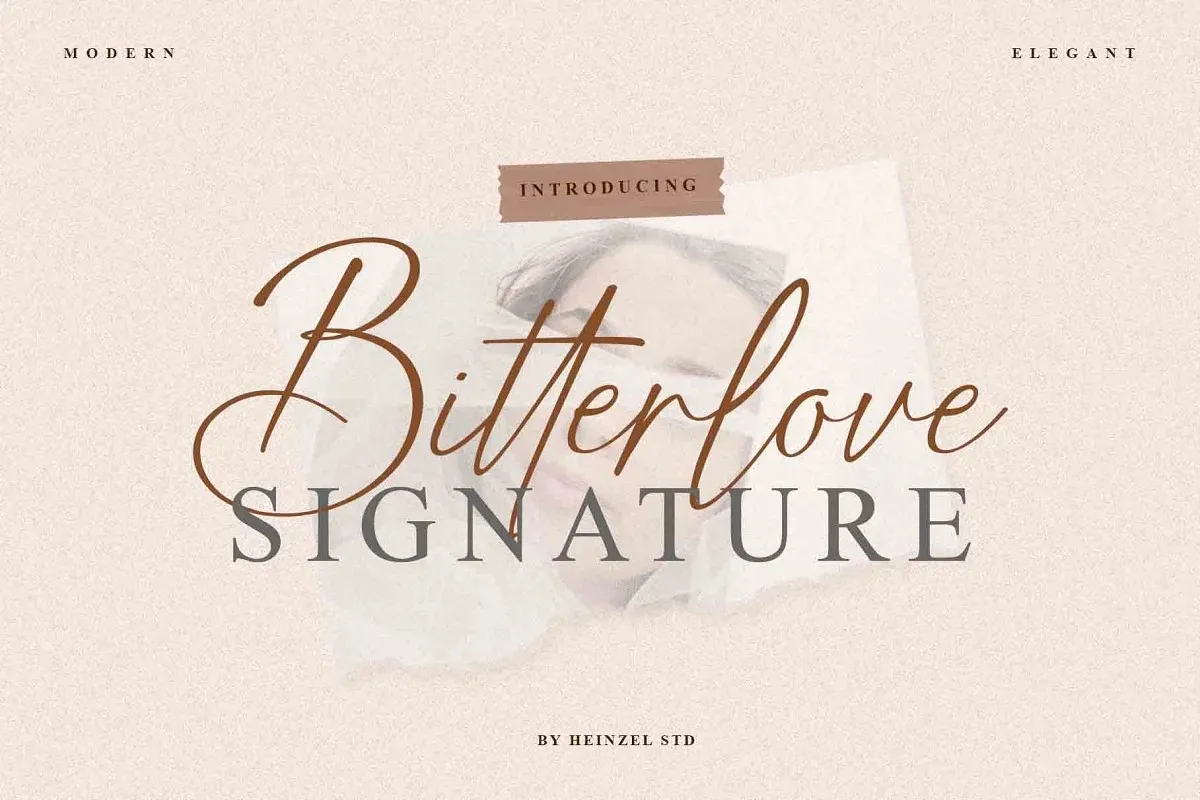
Bitterlove Script Font – Download Grátis
Esta é uma fonte script escrita a mão que foi criada pela Heinzel Std. É perfeitamente adequada para criar identidades visuais memoráveis e slogans de marcas. Suas características distintas e estilizadas tornam-a um recurso valioso tanto para logomarcas quanto para criações de citações ou outros elementos de design textual. A fonte ‘Bitterlove Script Font’ captura a essência delicada do estilo, trazendo ao seu projeto uma personalidade única e uma riqueza que irá chamá-lo para si. Adotar essa fonte é como dar aos seus projetos um toque de elegância e individualidade.